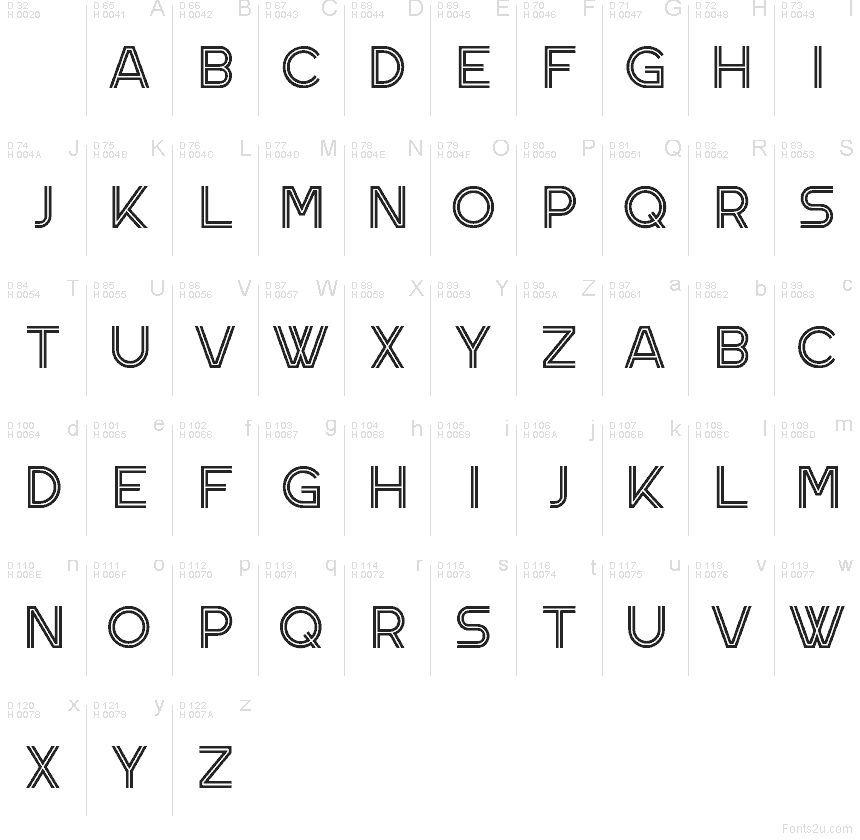
Fake Book, par Vladimir Nikolic, est une police d'affichage Art déco gratuite, caractérisée par de grandes capitales formées de doubles traits nets. Son allure est à la fois théâtrale et maîtrisée, mêlant diagonales tranchantes, courbes arrondies et espaces intérieurs ouverts qui rappellent le rythme des affiches d'époque et des enseignes lumineuses.
Elle est toute indiquée pour les couvertures de livres, l'identité visuelle de cafés, les affiches d'événements, les génériques ou la titraille de magazines, là où une police gratuite peut apporter une touche urbaine vintage sans en faire trop. Grâce à ses capitales aérées, elle fonctionne aussi très bien pour des monogrammes et des titres courts nécessitant une esthétique rétro épurée.